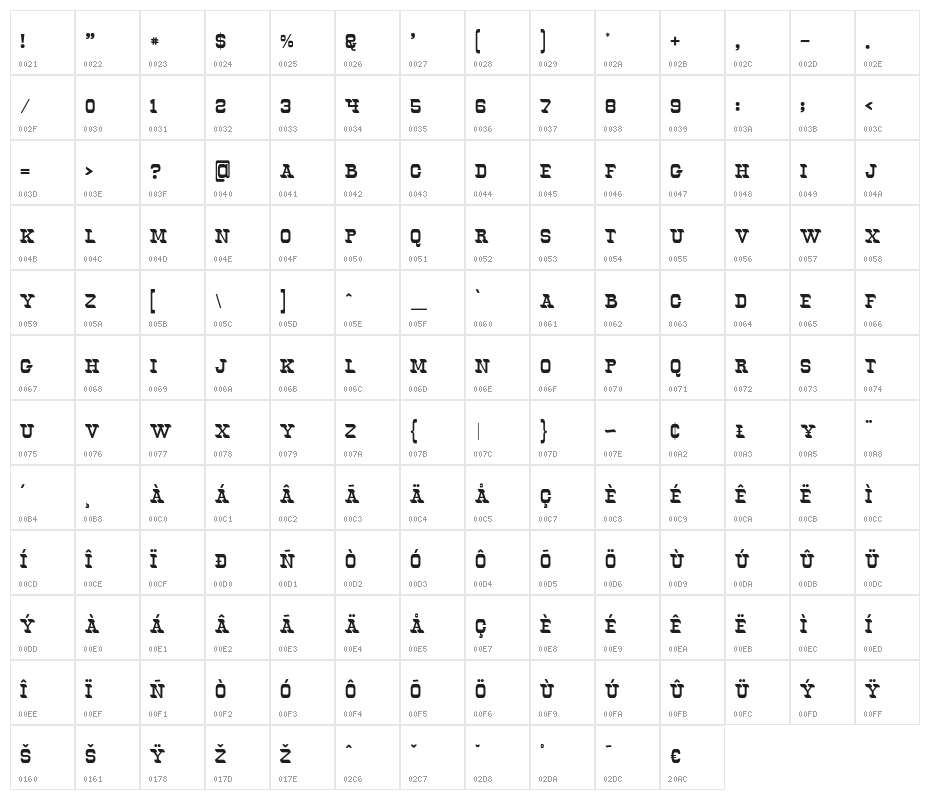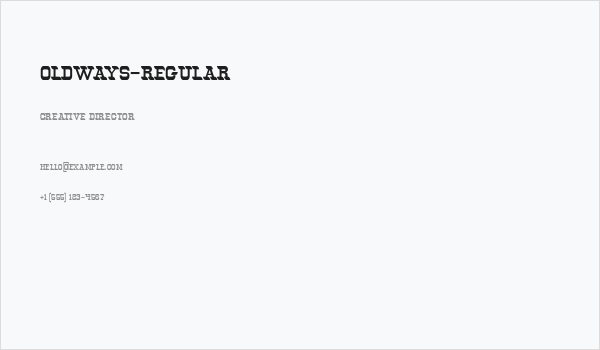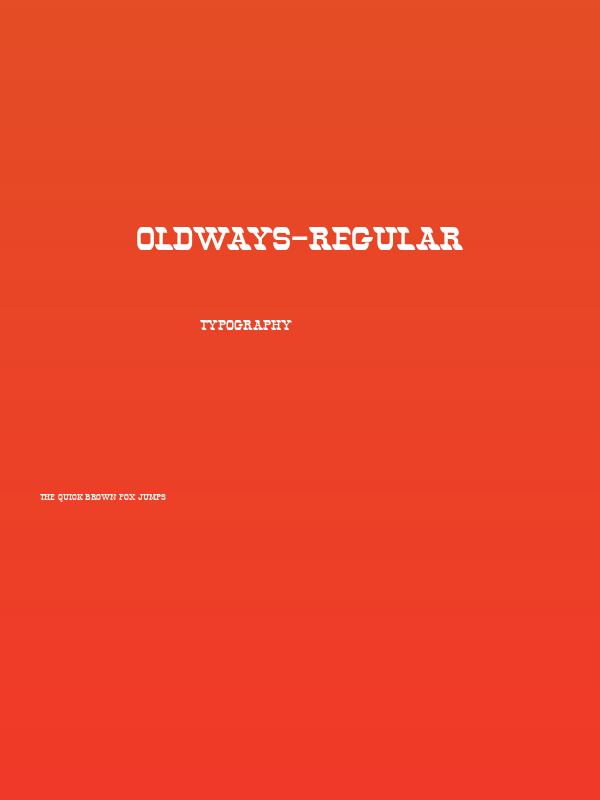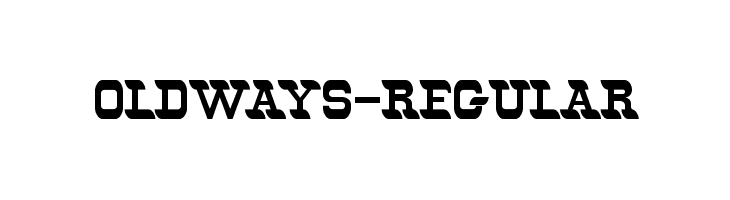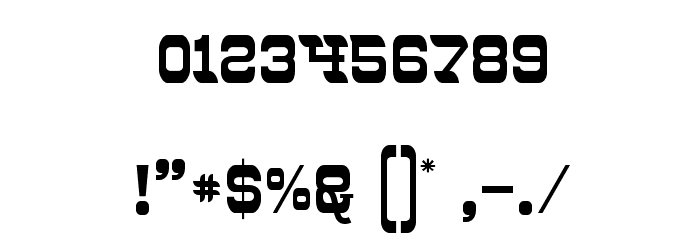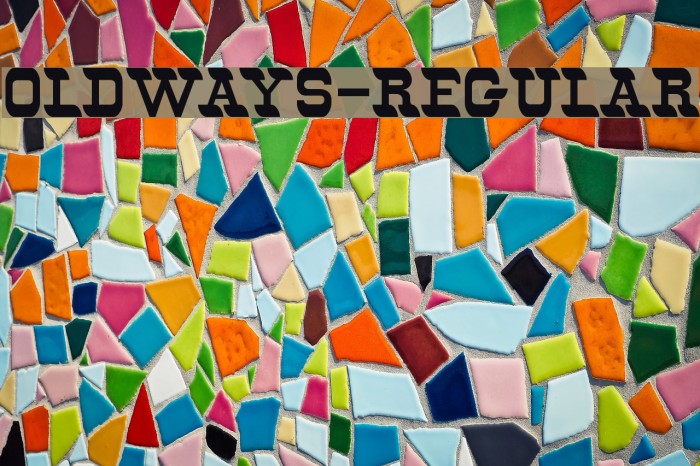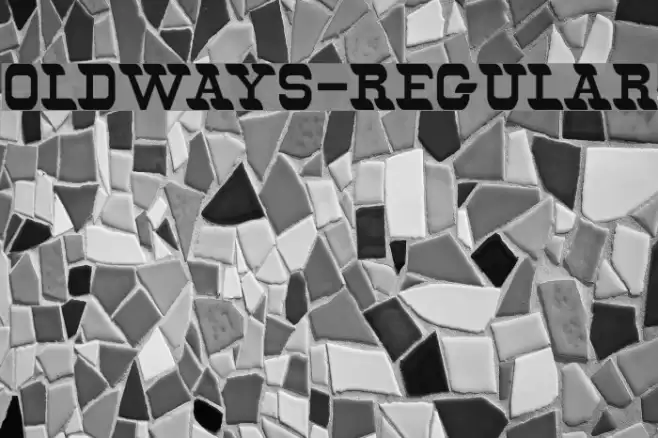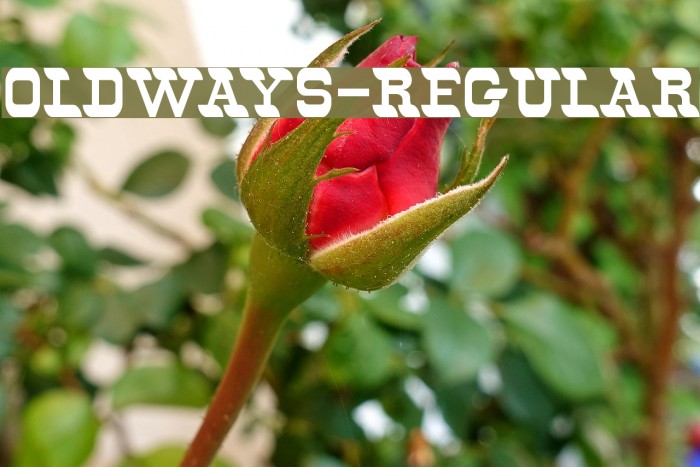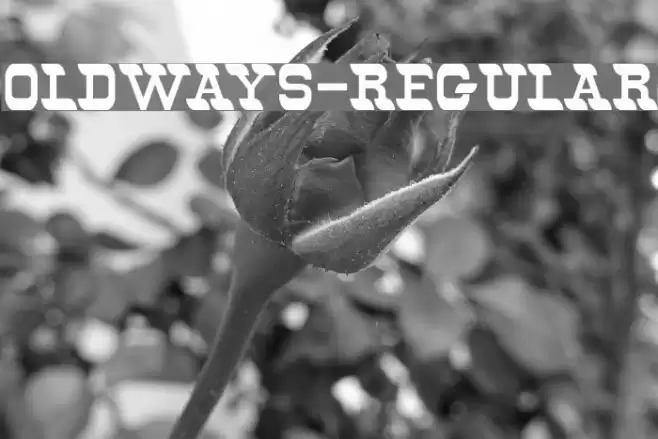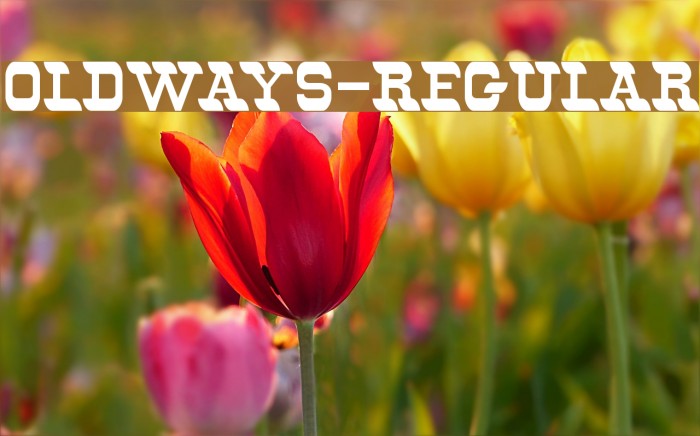
Oldways-Regular Font
✎ Serif
| Категория | Serif |
| Общий стиль | Vintage |
| Рекомендуемые проекты | Ideal for retro-themed posters, signage, branding, and headlines that require a strong visual impact. |